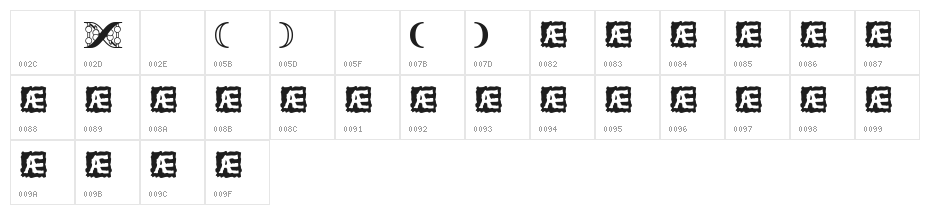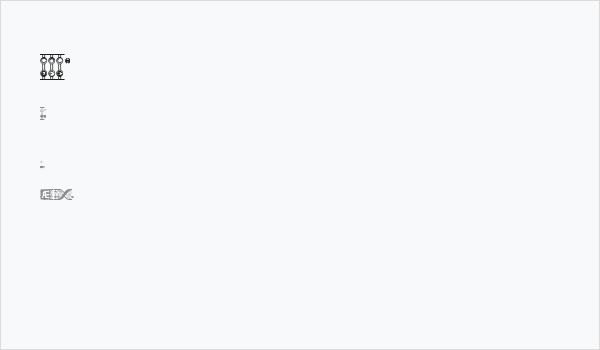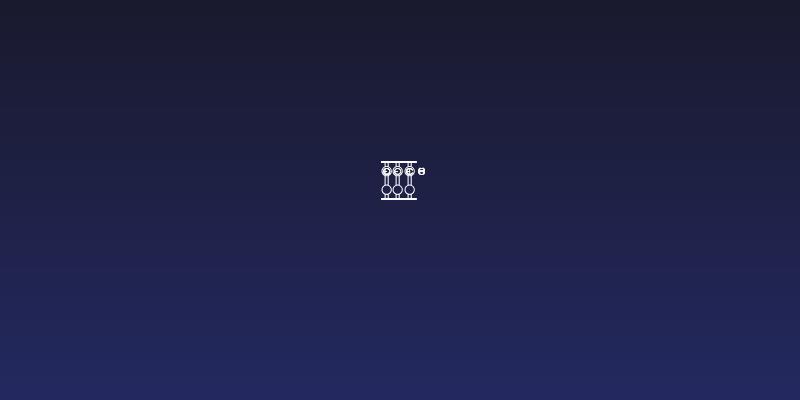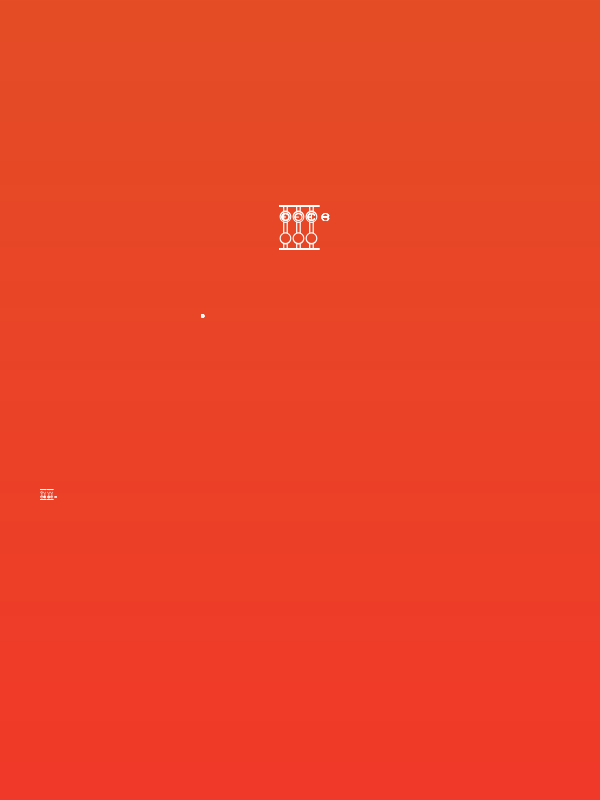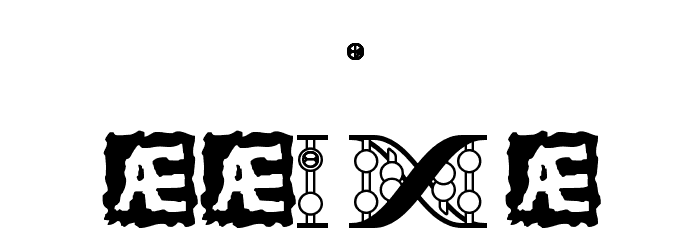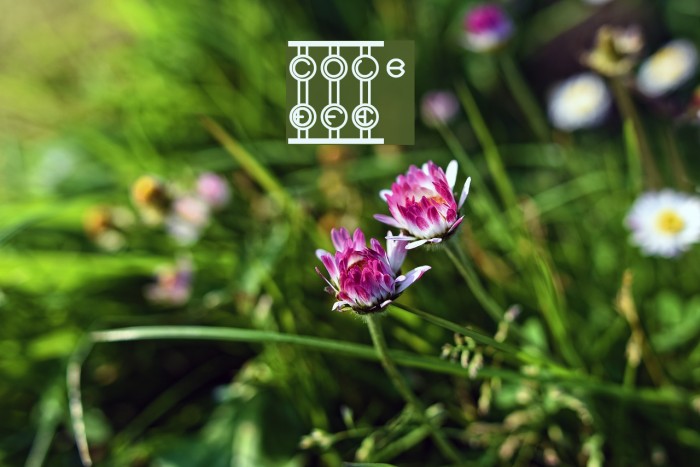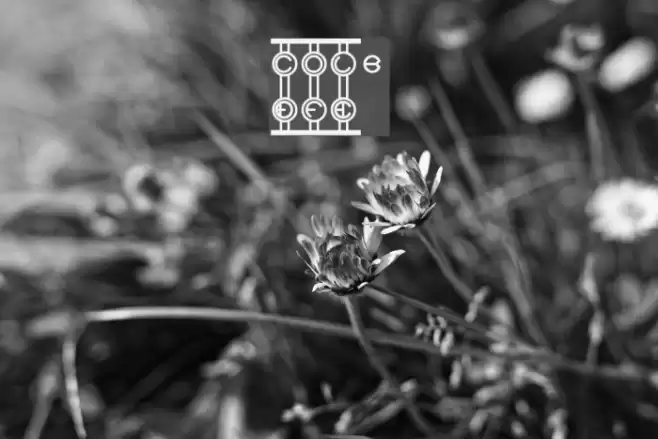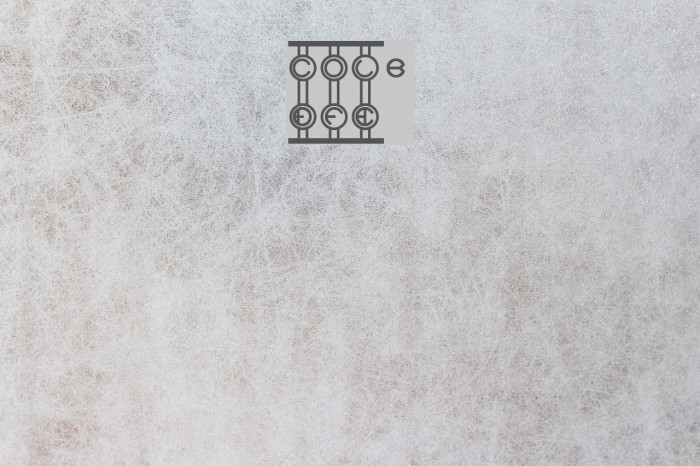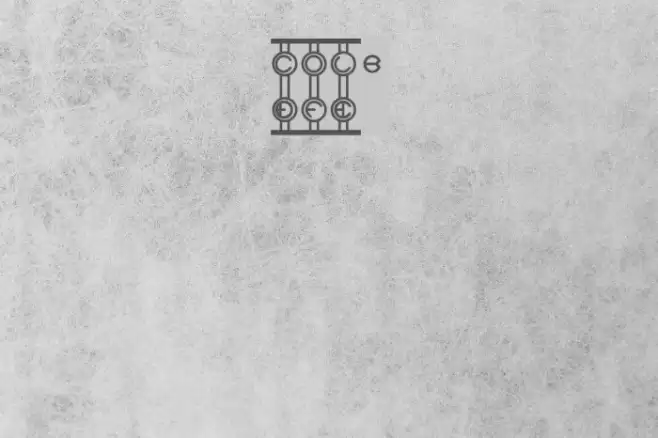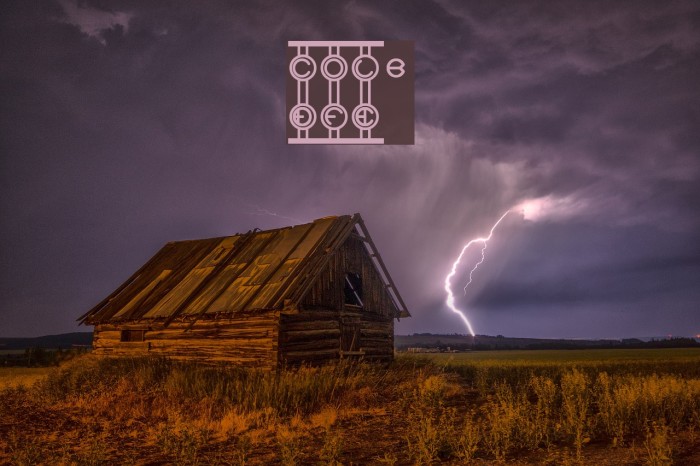
Code Of Life BRK Font
| 全体的なスタイル | Futuristic, Scientific |
| 用途 | Logos, Headlines |
| おすすめプロジェクト | Ideal for science fiction book covers, educational posters, and technology-themed branding. |